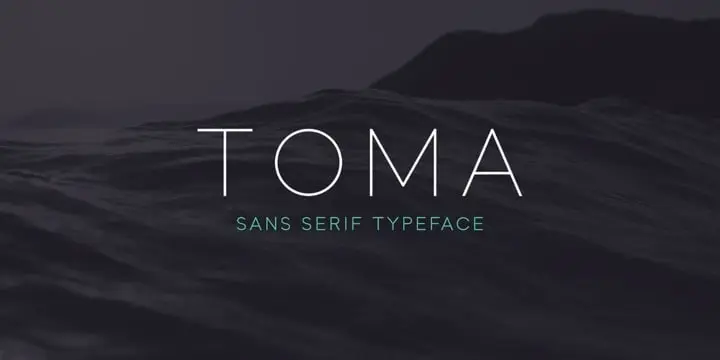
Toma Sans Font Family – Fonte Grátis
Toma Sans Font Family
Aqui está uma descrição envolvente para a página de download da fonte Toma Sans Font Family: Se você está trabalhando em um projeto de design, ciência ou até mesmo escrevendo um livro, não deixe de experimentar o poder do Toma Sans Font Family. Iremos apresentá-lo como uma nova família de fontes, perfeitamente adequada para seu trabalho. Inspirado no estilo geometrico dos sans serif que era popular nos anos 20 e 30, os Toma Sans foi projetados por JAM Type Design. Essa família de sete pesos de fonte, junto com suas itálicas, oferece uma grande variedade para personalizar seu projeto. Ideal tanto para um design simples quanto sofisticado, o Toma Sans é uma excelente escolha quando você busca mais de um estilo de escrita em sua página ou em seu layout gráfico. Ele combina elegância e facilidade na leitura com um toque moderno e contemporâneo.